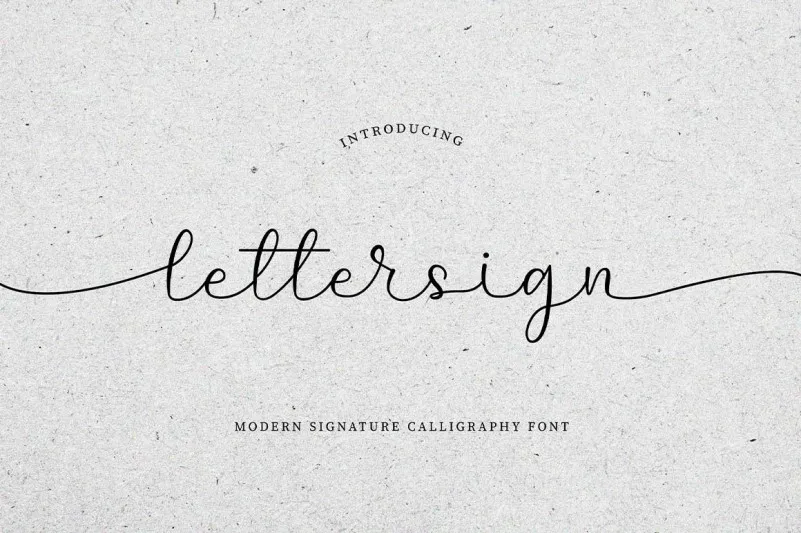
Lettersign Font – Download Grátis
Esta é outra elegante fonte de assinatura moderna, que mescla o estilo do antiguidade das caligrafias com uma roupagem moderna e atual. A fonte é PUA codificada, garantindo que você possa acessar facilmente todos os caracteres disponíveis, incluindo as versões em desenho chamadas swashes. Este é um verdadeiro tesouro para seus projetos futuros, como designs de convites modernos, estilos de correspondência de marca, casamentos e aniversários. É uma fonte perfeita para aqueles que buscam algo especial para adicionar charme a seus projetos, seja em impressão ou digital.